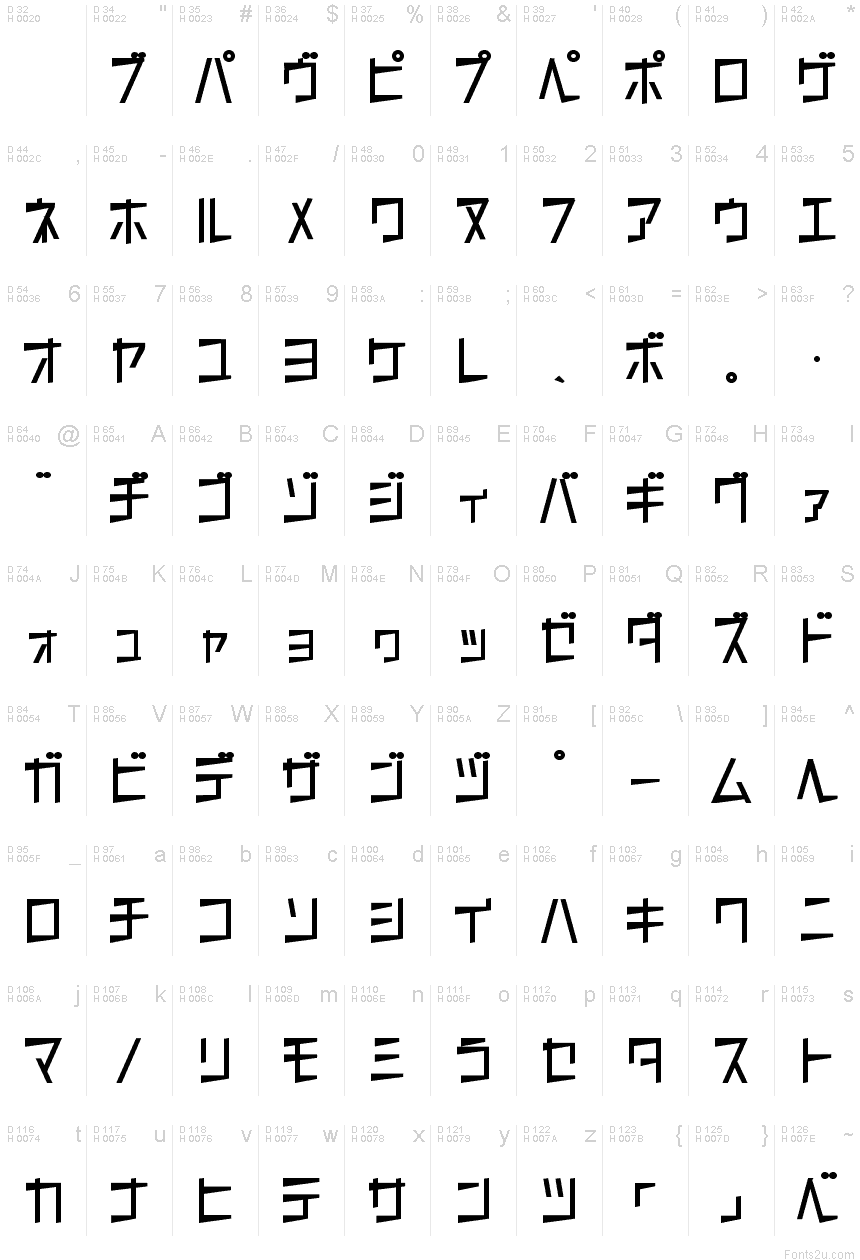
S K50kmh de Flop Design est une police d’affichage japonaise gratuite au style tranchant, évoquant la vitesse des katakana. Les lettres semblent découpées dans des barres rigides avec des traits anguleux, conférant à la police un rythme mécanique épuré. Son esthétique se prête davantage à la signalétique, à l’identité visuelle technologique et au motion design qu’aux styles manuscrits ou doux.
Elle est idéale pour les titres d'affiches, les interfaces de jeux, les designs musicaux, le streetwear et les cartons de titre où ce dynamisme urbain fait toute la différence. En tant que police gratuite, elle est également parfaite pour les logos courts, les titres d'accroche et les en-têtes marqués, car sa géométrie brute et ses coupes inclinées donnent une impression d’énergie et de direction même aux mots les plus brefs.
Table des caractères de la police S K50kmh
Table des caractères de S K50kmh : Latin de base, page 1
Glyphes de la police S K50kmh — Latin de base, page 1